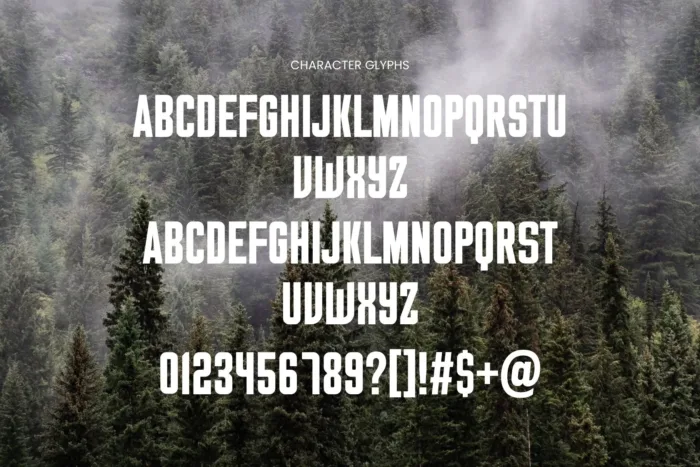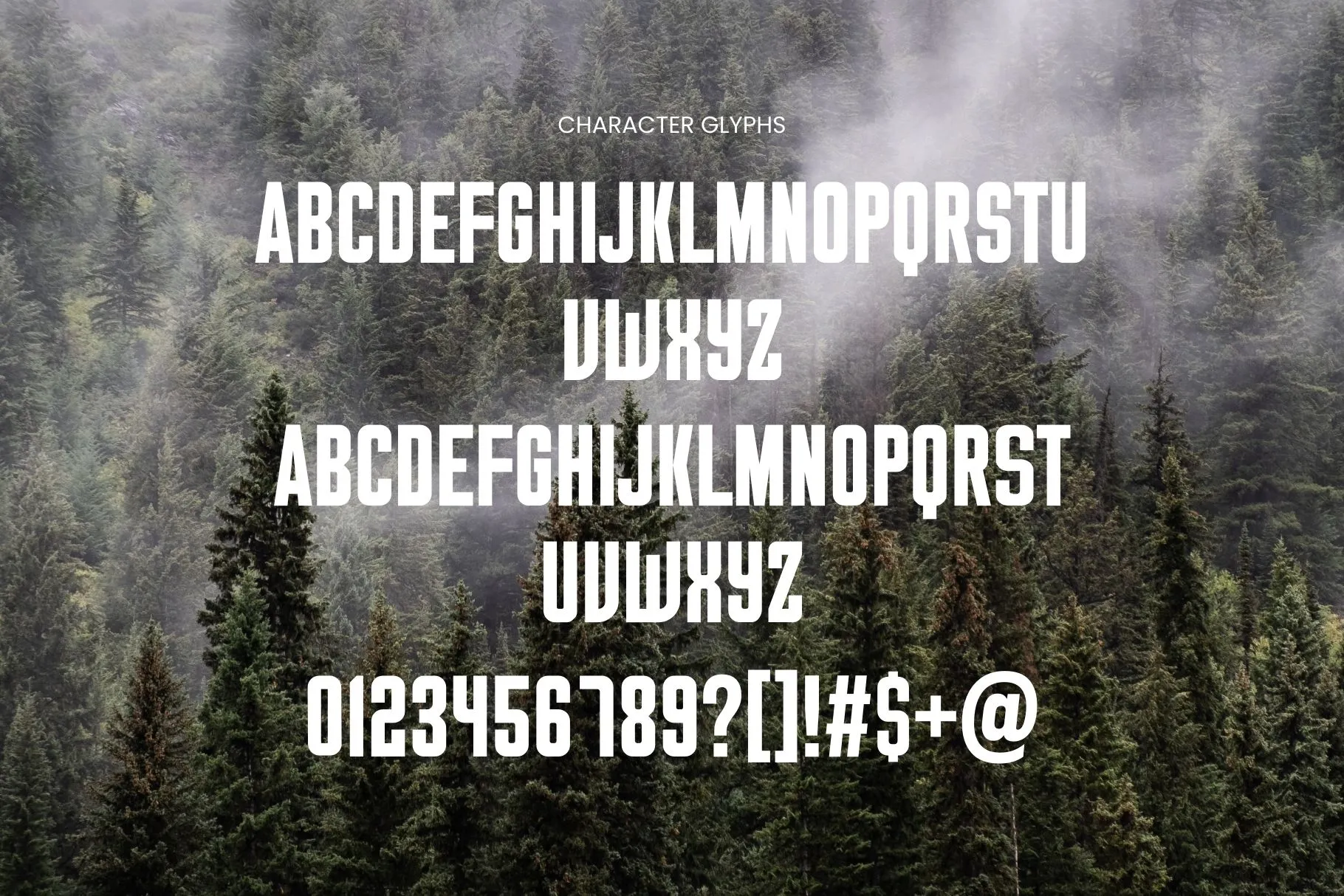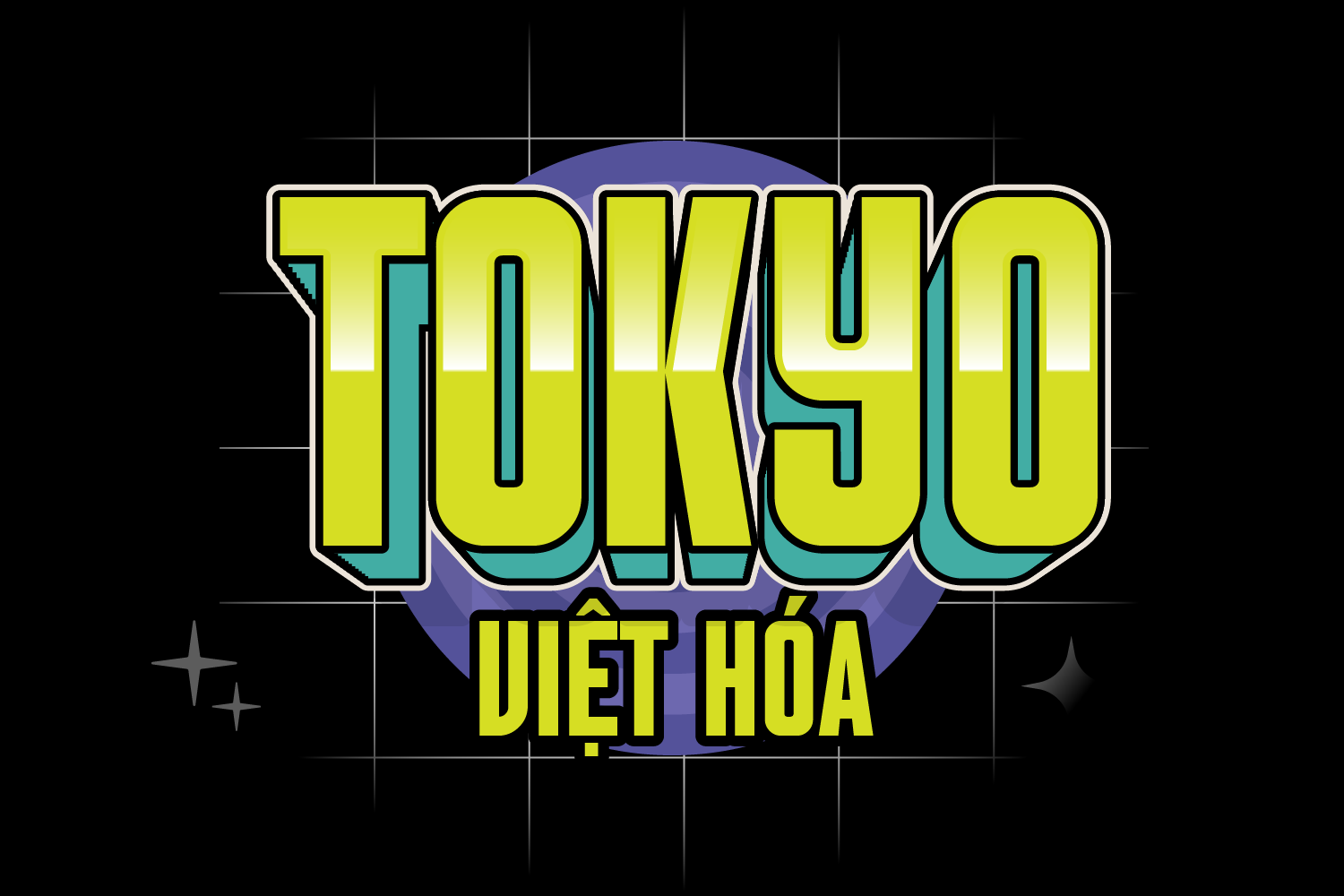
DVN Tokyo Việt hóa – Font chữ đậm chất đô thị, cá tính và hiện đại
Font Tokyo Việt hóa mang đậm tinh thần của những con phố sôi động và ánh đèn rực rỡ nơi đô thị. Với thiết kế chữ đậm – hẹp – mạnh mẽ, font này tạo nên cảm giác hiện đại, thời thượng nhưng vẫn giữ được nét cá tính rất riêng.
Các nét chữ vuông vức, bo nhẹ ở góc giúp tổng thể vừa cứng cáp vừa mềm mại — giống như nhịp sống nhộn nhịp của Tokyo: mạnh mẽ nhưng đầy tinh tế. Khi dùng cho tiêu đề, poster hay thiết kế thương hiệu, Tokyo sẽ khiến mọi ánh nhìn phải dừng lại.
👉 Đây là lựa chọn lý tưởng cho các dự án thiết kế sáng tạo: từ poster sự kiện, branding thời trang, bìa tạp chí, cho tới các thiết kế mang chất street style hoặc retro hiện đại.